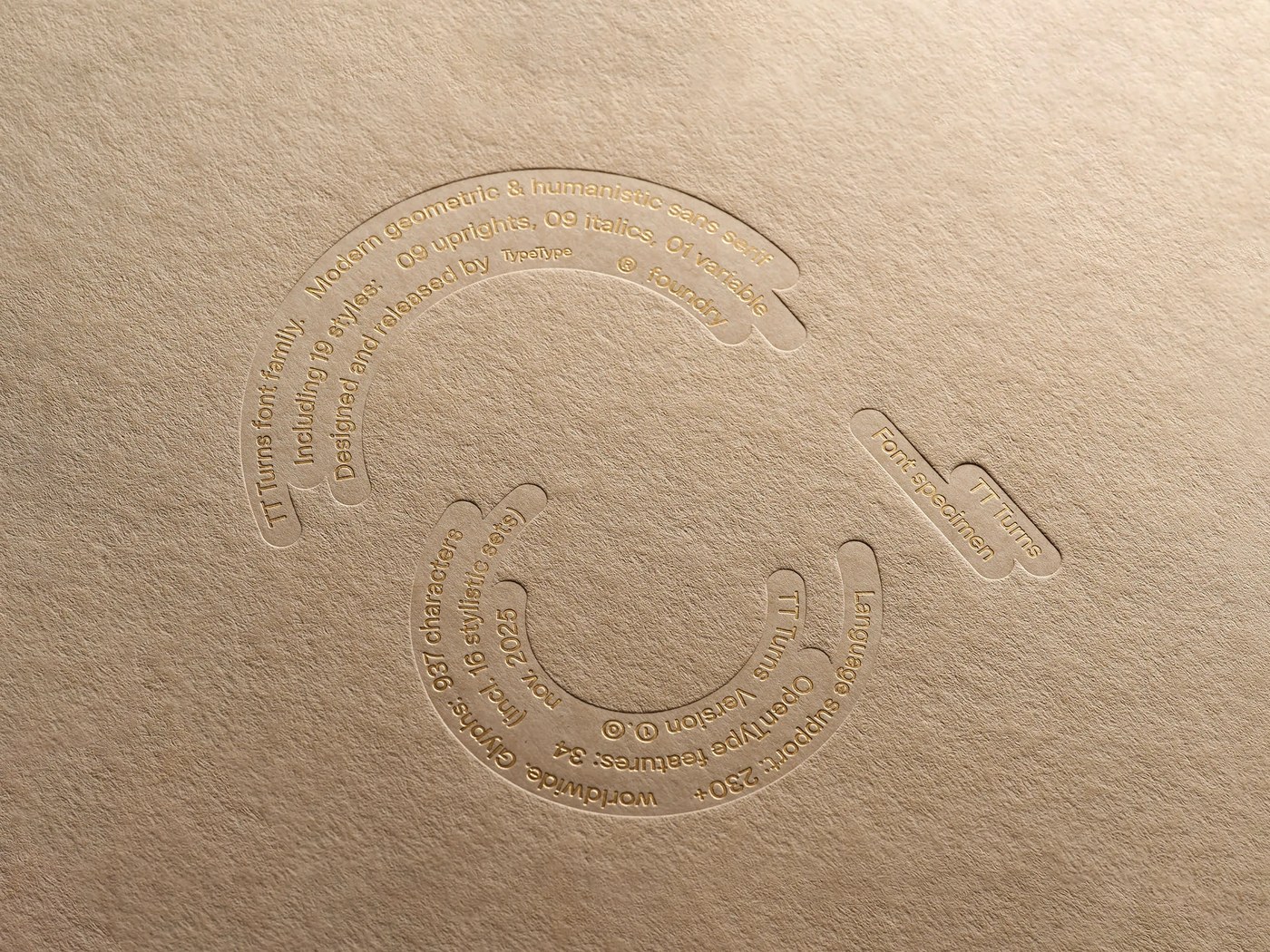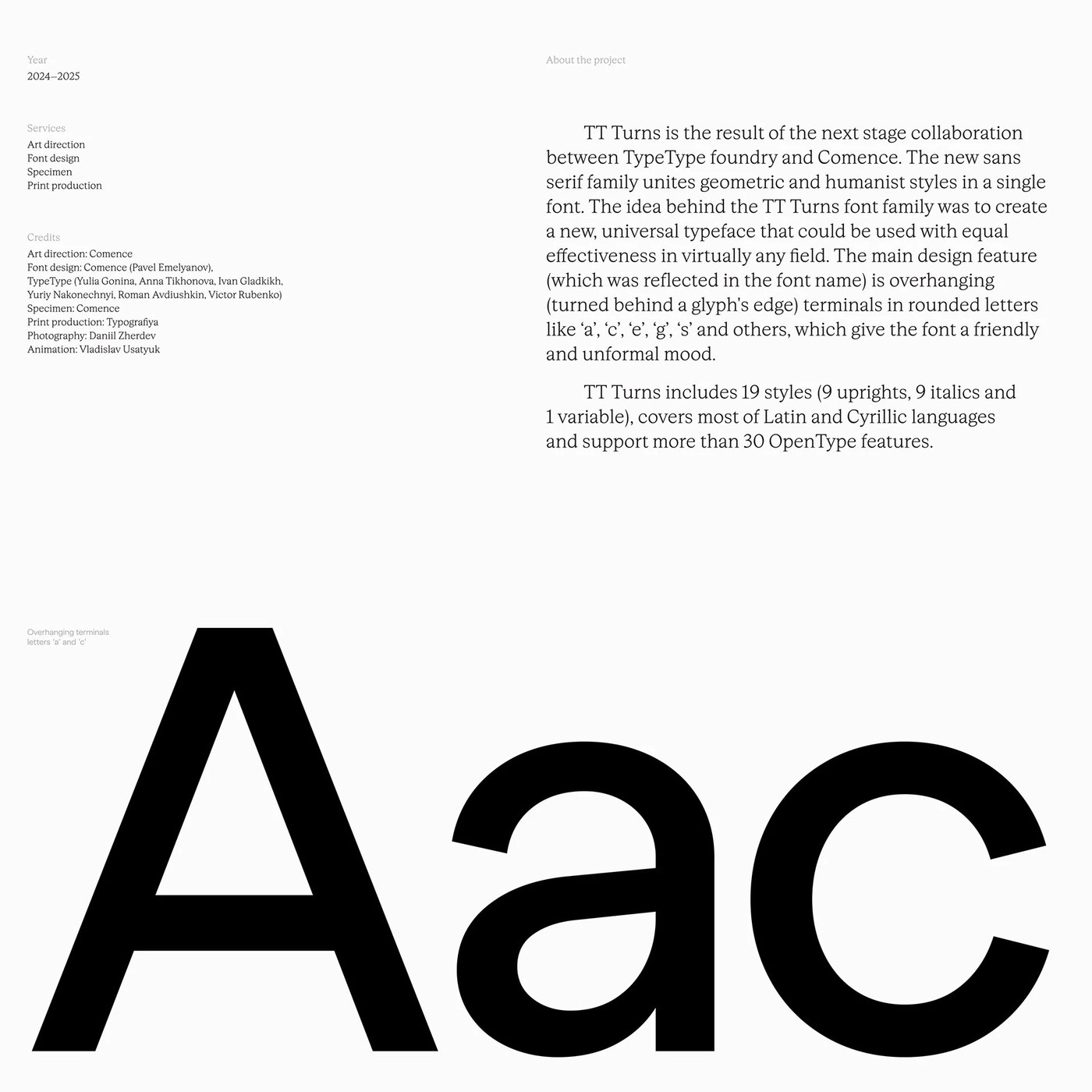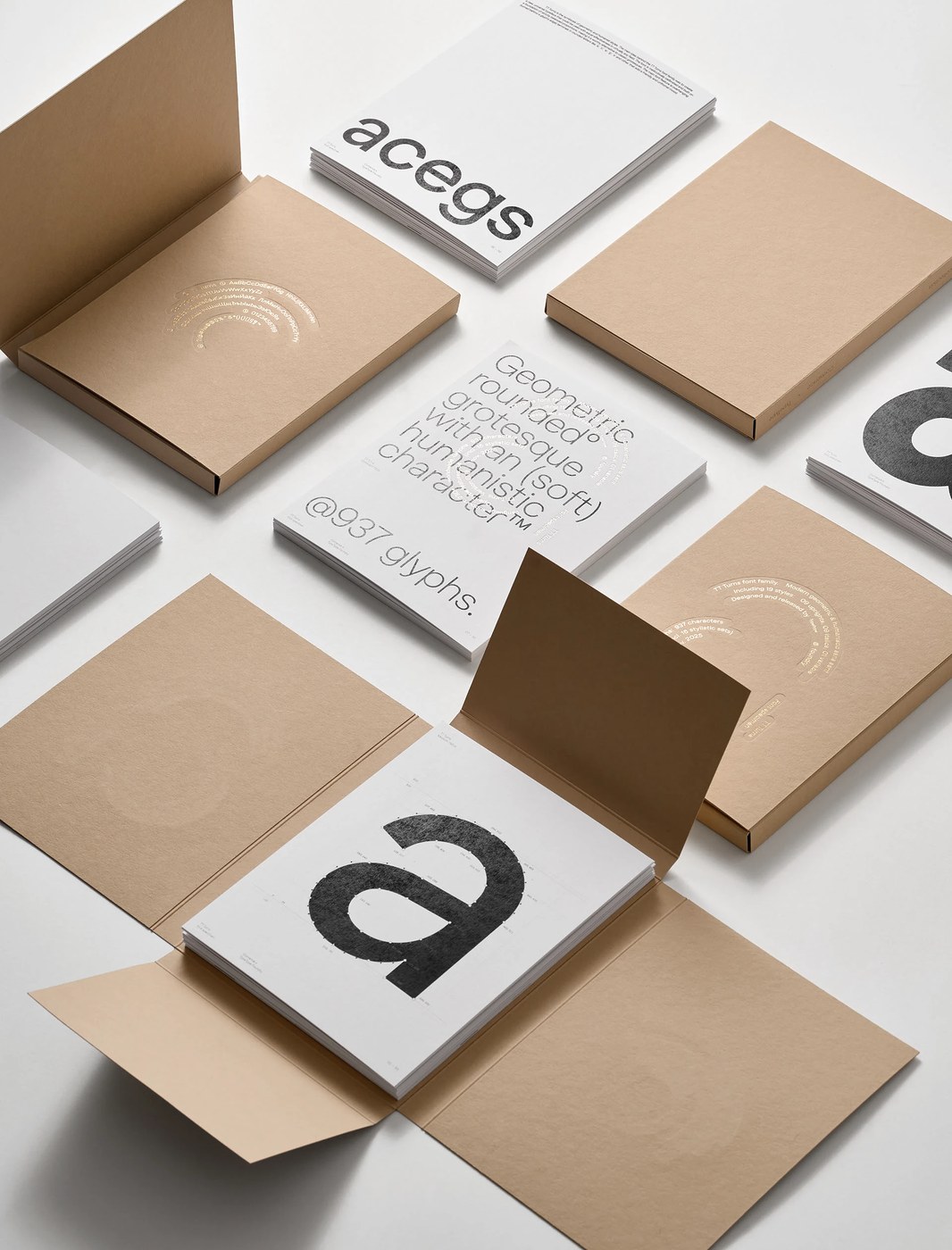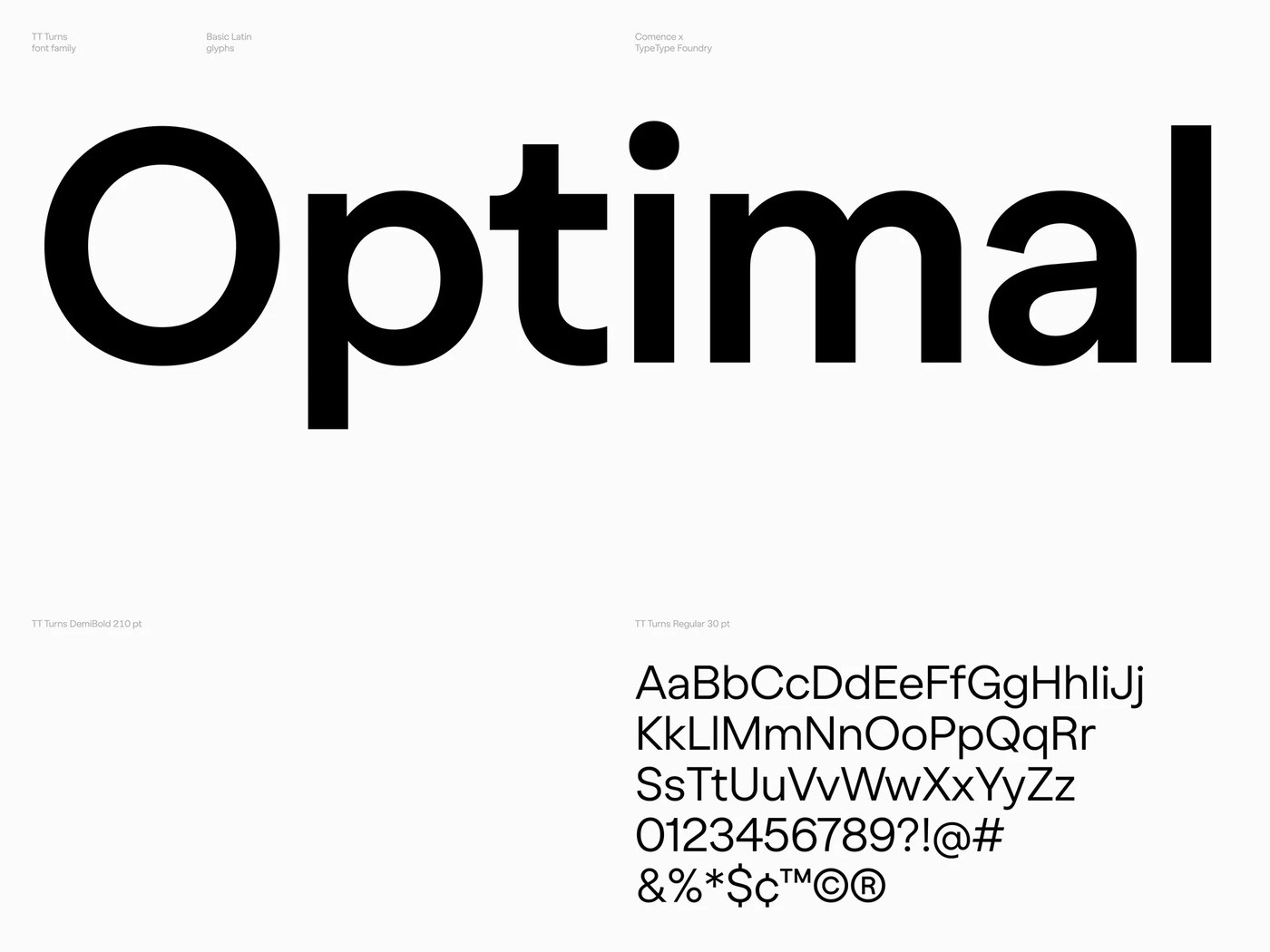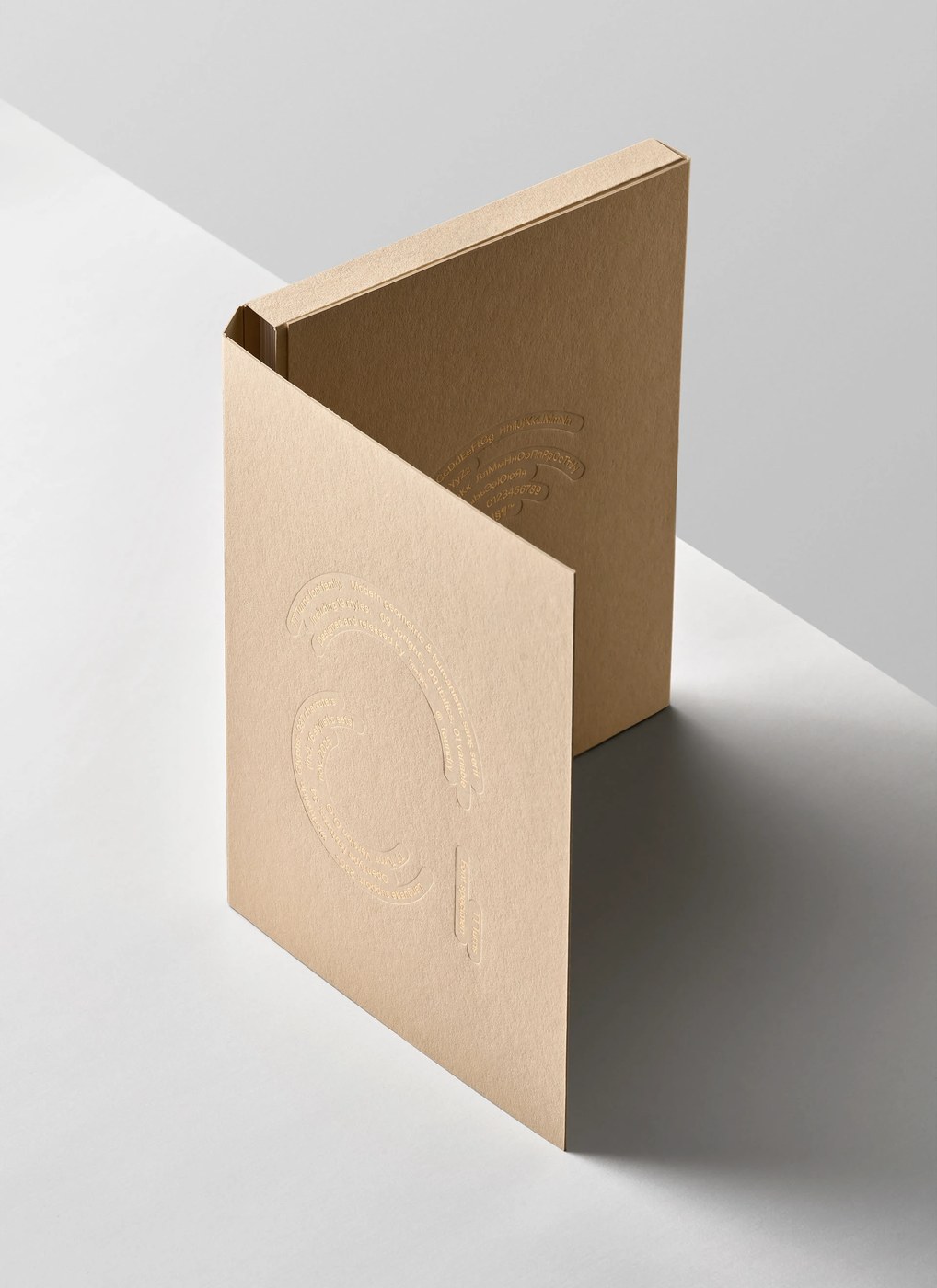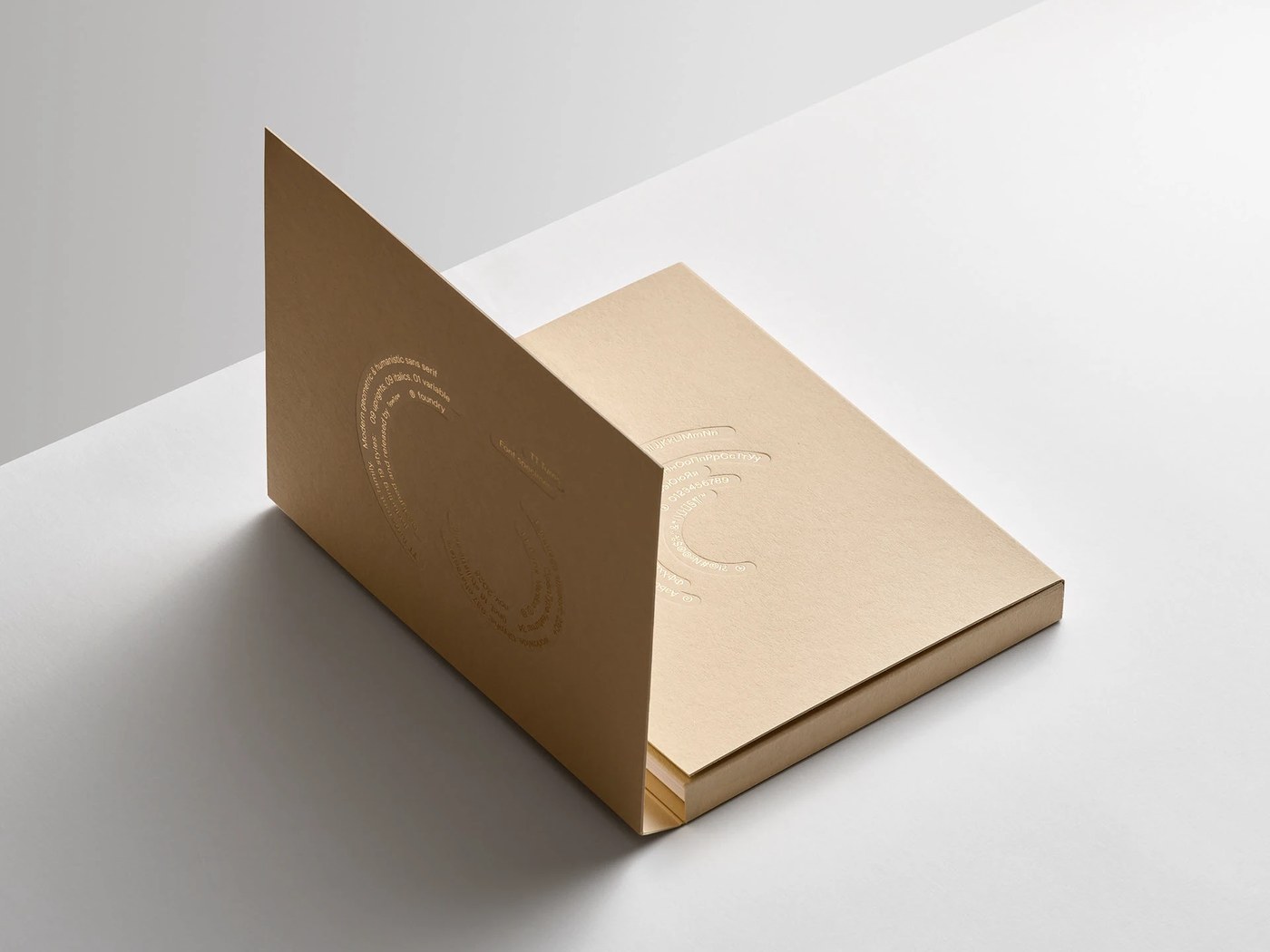
Bộ font chữ sans serif bo góc biến thể (variable font) TT Turns của Pavel Emelyanov là sự kết hợp hài hòa giữa cấu trúc hình học và nhịp điệu tự nhiên trên nền chất liệu giấy ấm áp.
Mỗi đường nét con chữ đều thể hiện sự căn lề baseline chuẩn chỉnh và tuân thủ các quy tắc hình học nghiêm ngặt. Hệ thống lưới modular hỗ trợ tới 19 định dạng (style) khác nhau trên cùng một trục độ dày (weight axis). Hệ thống phân cấp cấu trúc này đảm bảo trải nghiệm đọc cực kỳ rõ ràng ở mọi kích thước. Những đường cong xoay ngược độc đáo tạo nên một nhịp điệu thị giác mới mẻ cho các layout thiết kế thông thường.
Bố cục độ tương phản cao
Bản in thử (specimen) trên giấy kraft tôn vinh kết cấu thô mộc của chất giấy ấm áp hòa quyện cùng sắc mực đen. Sự tương phản rõ rệt này hướng sự chú ý của người xem vào cấu trúc hình thể của con chữ hơn là phong cách trang trí. Kiểu dáng các ký tự vẫn giữ nguyên được thế mạnh trên cả hệ chữ Latin và Cyrillic. Phần đuôi chữ xoay ngược luôn đồng bộ trên tất cả các glyph.
Tỷ lệ typography hiển thị vô cùng vững chắc trong cả layout biên tập (editorial layout) lẫn môi trường giao diện. TypeType Foundry đã biến tác phẩm này thành một công cụ thiết kế vô cùng hữu ích. Để tìm hiểu thêm thông tin, mọi người có thể xem qua www.behance.net/gallery/245068053/TT-Turns-Font-Specimen.
Bố cục sử dụng những khoảng trống (negative space) rộng rãi để tạo ra sự tương tác đầy chủ đích giữa các thành phần. Lựa chọn cấu trúc này giúp tôn vinh các hình dáng con chữ một cách tỉ mỉ nhất. Trọng lượng thị giác được giữ cân bằng hoàn hảo, mỗi glyph đều đứng vững vàng tại vị trí của mình. Kết quả mang lại là một hệ thống typography vô cùng ngăn nắp và chỉn chu.
Pavel Emelyanov’s TT Turns is a striking rounded geometric sans-serif variable font that beautifully balances clean geometry with a natural rhythm, all showcased against warm paper textures.
Every single stroke highlights flawless baseline alignment and strict geometric precision. Built on a modular grid, the family offers 19 different styles running along a flexible weight axis. This structural hierarchy guarantees crystal-clear readability at any size, while the unique inverted curves inject a fresh visual rhythm into everyday design layouts.
High-Contrast Layouts
The printed font specimen on kraft paper celebrates the raw texture of warm paper stock paired with deep black ink. This bold contrast locks the viewer’s focus directly onto the actual anatomy of the letterforms rather than decorative flair. The character shapes hold their ground beautifully across both Latin and Cyrillic alphabets, keeping those signature inverted tails perfectly consistent across the entire glyph set.
Typographic proportions feel incredibly solid, effortlessly adaptive for both editorial layouts and digital user interfaces. The team at TypeType Foundry has truly turned this release into a versatile, high-utility design tool. For a deeper dive into the project, check out the www.behance.net/gallery/245068053/TT-Turns-Font-Specimen.
The layouts make use of generous negative space to create a highly intentional interaction between design elements. This structural choice gives the meticulously crafted letterforms plenty of room to shine. Visual weight is balanced to perfection, ensuring every single glyph stands firmly in its place to deliver a clean, impeccably organized typographic system.